今回は、レトロゲーム「ファミコンゲーム」のような世界観ぴったりのおすすめフォントをまとめてみました。
ファミコンようなレトロなゲームは、表現できる画素数や解像度が限られていたので、⽂字の形を正⽅形のドット(ピクセル)で表現されたフォントを使うのが当たり前でした。
そんなドット(ピクセル)で表現されたフォントを見るとどうしてもレトロなゲームを想起してしまいますね。現代でも、デザインのアクセントやあえてレトロなトーンを作りたい際に使うこともあります。
今回はそんなレトロゲーム「ファミコンゲーム」にぴったりなフォントをご紹介します。
「ファミコンゲーム」におすすめの日本語フリーフォント
以下のサンプル画像は、本記事で紹介しているフォントの一部です。レトロなゲーム感ぽさがぴったり表現できて、素敵なフォントばかりなので、ぜひ参考にしてみてください。
マルミーニャ
マルミーニャフォントは、12ピクセルサイズをベースにした、丸ゴシック体のピクセルフォントです。
丸ゴシックタイプのピクセルフォントは珍しく、ピクセルフォントならではの「レトロさ」の中に「かわいさ」と「まじめさ」を感じるフォントです。
ドットゴシック16
ドットゴシック16(DotGothic16)フォントは、ガラケー時代の携帯の画面や、Windows98などの古いパソコンで使わていたフォントを表現したいというユーザーからの要望に応え、16×16のゴシック体のビットマップとして作られたフォントです。
ベストテンFONT
ベストテンFONTは、懐かしいレトロなゲームを思い出す10×10で作られているドットフォントです。
少し丸みがある丸文字となっている珍しいスタイルのピクセルフォントです。
魔導太丸ゴシック
魔導太丸ゴシックフォントは、ゲーム「ぷよぷよ」や「魔導物語」などのゲーム画面で使用していた文字を再現して作られたドット・ピクセル系フォントです。
美咲ゴシック
美咲ゴシックフォントは、 8×8 ドットで作られているのが特徴のピクセルフォントです。8×8マスのドットで制作されているので、他のピクセルフォントより少ないドットで作られています。
まるきやフォント
まるきやフォントは、太さに強弱が付いている特徴を持つ可愛らしいピクセルフォントです。
どんぐりデュエル
どんぐりデュエルフォントは、他のピクセルフォントに比べて太いウェイトでコロコロとした可愛いピクセルフォントです。太さとピクセルデザインがとてても可愛いらしい仕上がりとなったフォントです。
横浜ドット
横浜ドットフォントは、太めにデザインされた可愛らしい雰囲気を感じるピクセルフォントです。
マルモニカ
マルモニカフォントは、親しみやすい「柔らかさ」とシュッとしている「シリアスさ」を併せ持つピクセルフォントです。
マルモニ改変
マルモニ改変フォントは、上記で紹介している「マルモニカ」フォントをベースとして、角丸・斜体・ソリッドなど10種類以上のバリエーションに展開されたピクセルフォントです。
Melonano(メロナーノ)
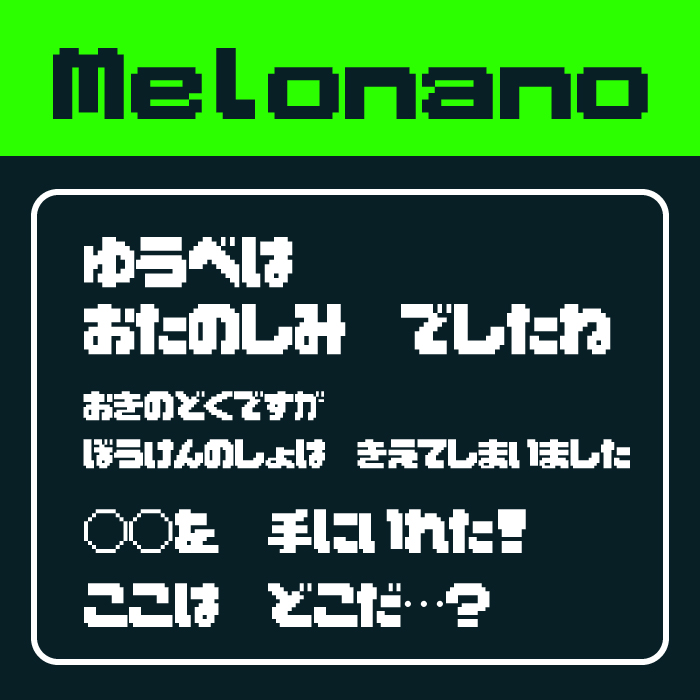
Melonano(メロナーノ)フォントは、コミカルで可愛らしい極太なピクセルフォントです。
縁架ドットゴシック24
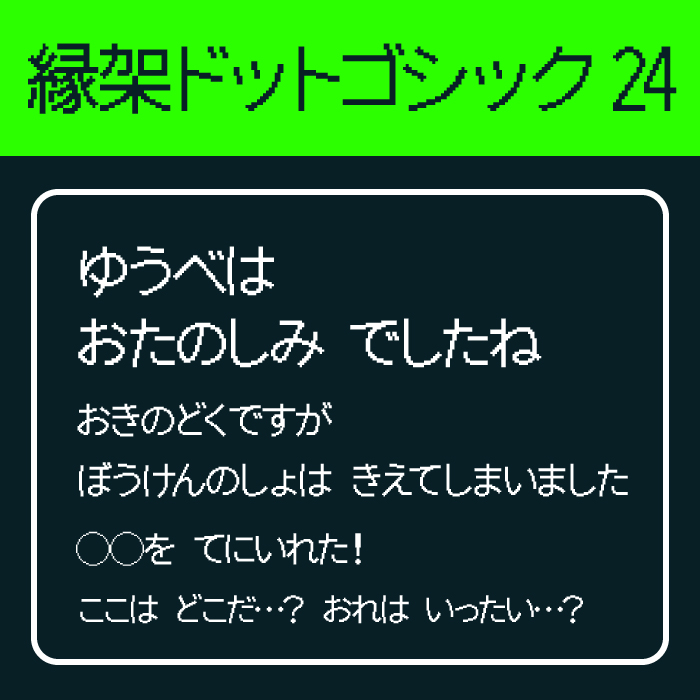
縁架ドットゴシック24 / 縁架ドット明朝24フォントは、「Noto Sans/Noto Serif」をベースに一文字ずつドット手打ちで制作されたドット風デザインフォントです。
ザ・ストロングゲーマー
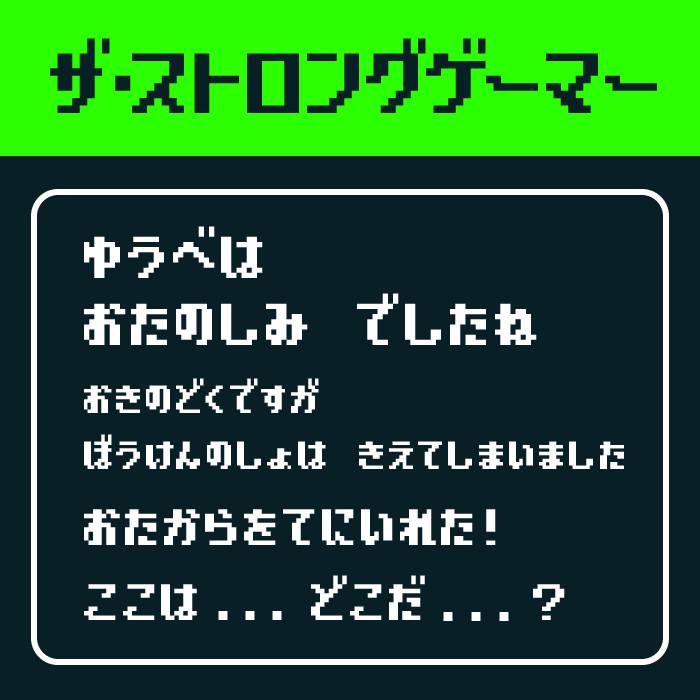
ザ・ストロングゲーマーフォントは、太めでカクカクしたドット調でレトロゲームの世界観にぴったりなピクセルフォントです。
チェックポイント.(ピリオド)
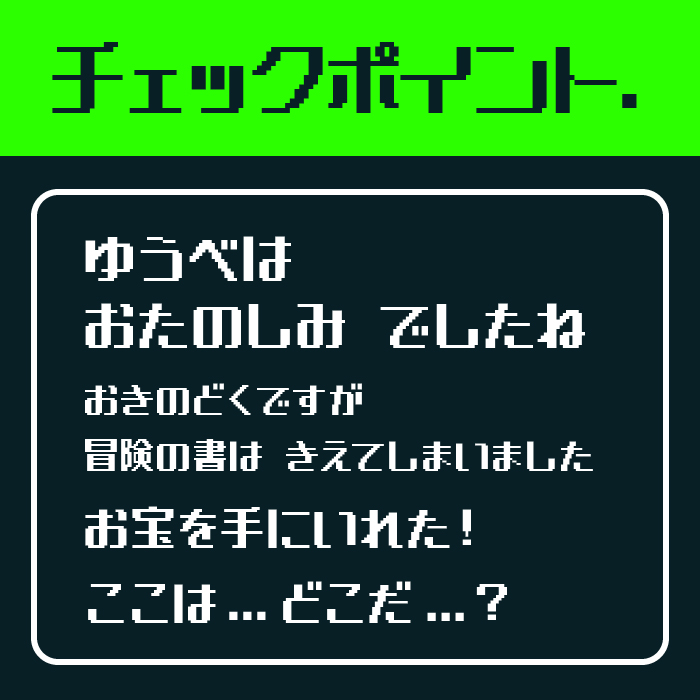
チェックポイント.(ピリオド)フォントは、「チェックポイント」フォントをベースとして、ビットマップフォント風に再構築して制作されたドットフォントです。
しかくふと
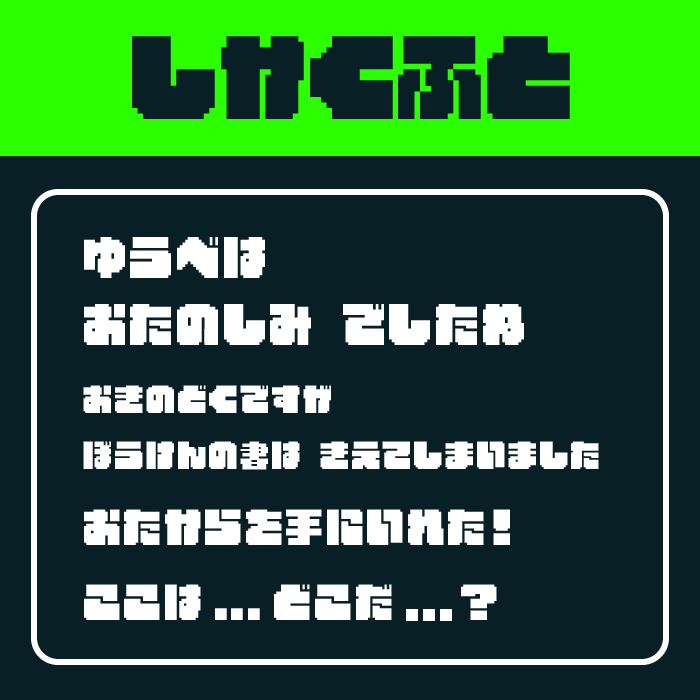
しかくふとフォントは、ブロックを削って作られたような超極太なピクセル感のあるデザインフォントです。